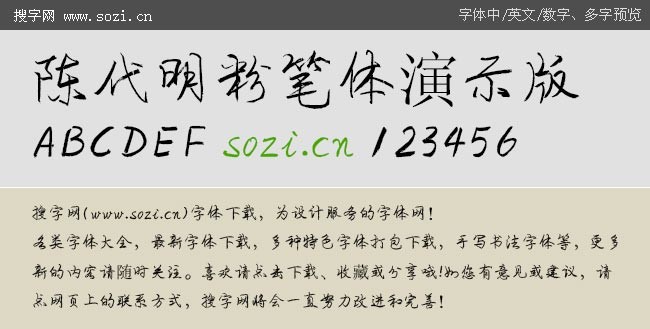
陳代明粉筆體演示版
搜字網(wǎng)提供一款陳代明粉筆體演示版中文書法字體下載。陳代明粉筆字體,是陳代明字體系列的最新版。作者陳代明,四川省硬筆書法家協(xié)會會員,中學(xué)高級教師,先后創(chuàng)作陳代明硬筆字體、硬筆字體精修版(書香體)和方正字跡陳代明行楷體。本網(wǎng)站的陳代明粉筆體是一個演示體驗版,有部分字缺失,該字體擁有正規(guī)版權(quán),對本字體感興趣的朋友請向作者聯(lián)系。QQ:641457046。電話:13194796177。微信號:chdm63。加時請注明來自搜字網(wǎng)。